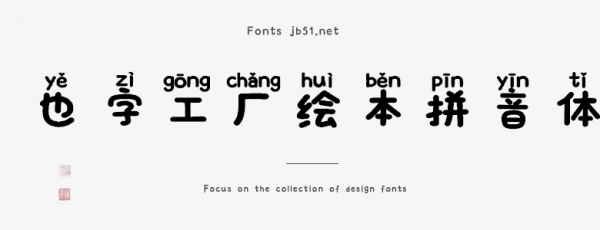
也字工廠繪本拼音體是由也字工廠出品的藝術(shù)字體,字體筆觸略顯粗實(shí),字形圓潤(rùn),具有很好的視覺(jué)感,適合應(yīng)用于藝術(shù)設(shè)計(jì)、平面宣傳設(shè)計(jì)、網(wǎng)頁(yè)設(shè)計(jì),書(shū)法字帖等領(lǐng)域,需要的朋友可以前來(lái)本站下載。